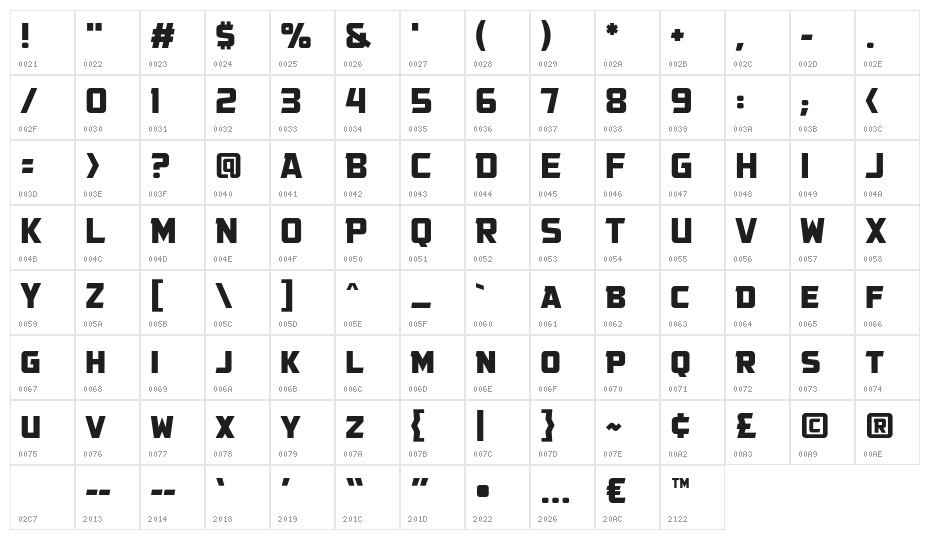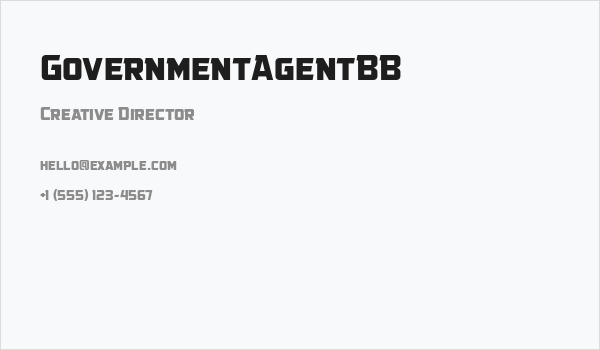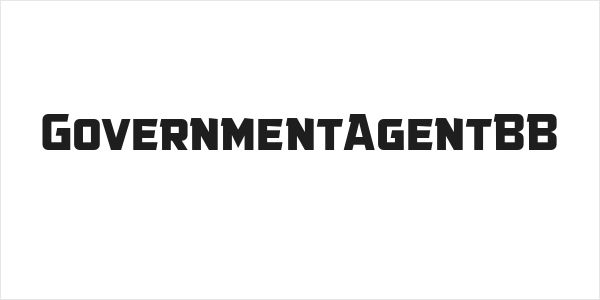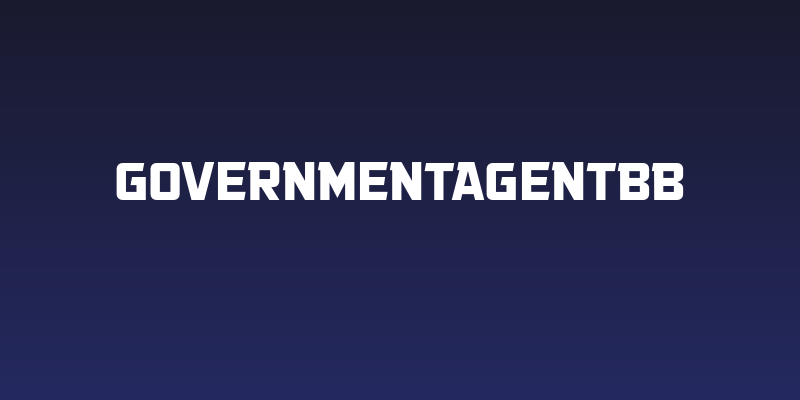
GovernmentAgentBB Font
| Vorgeschlagene Projekte | Ideal for branding, signage, posters, and headlines where a strong, modern presence is required. |